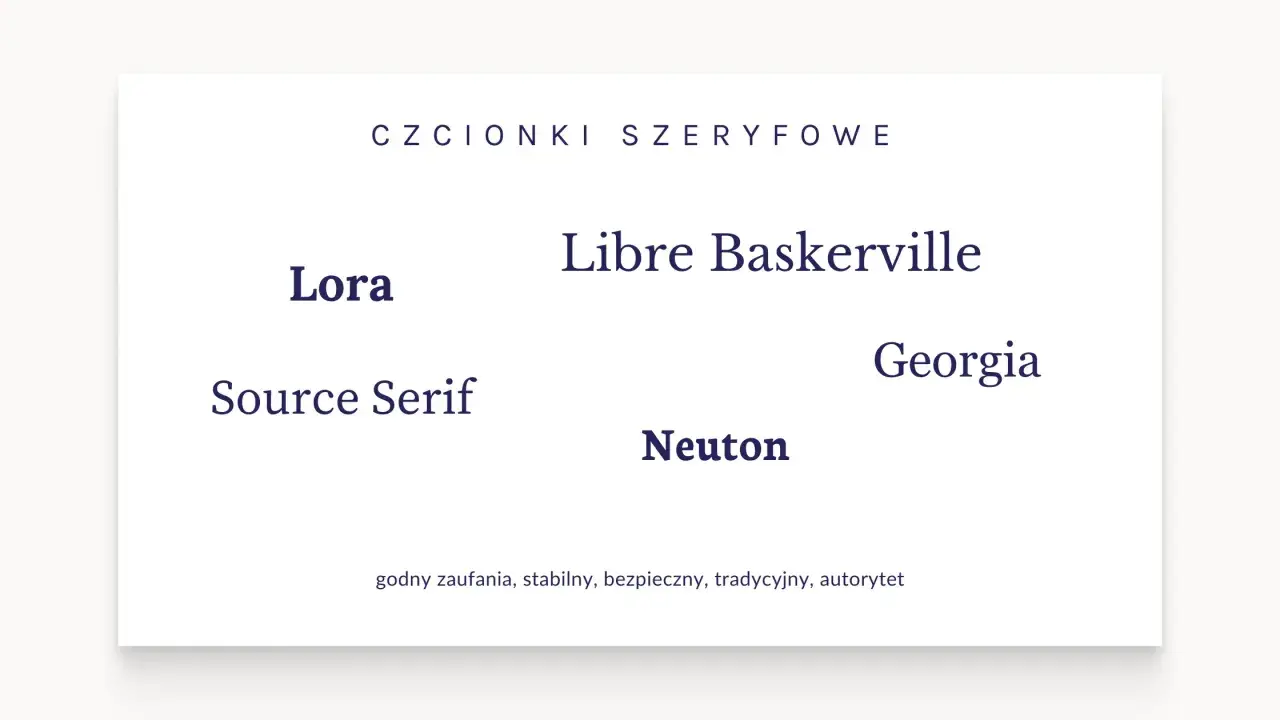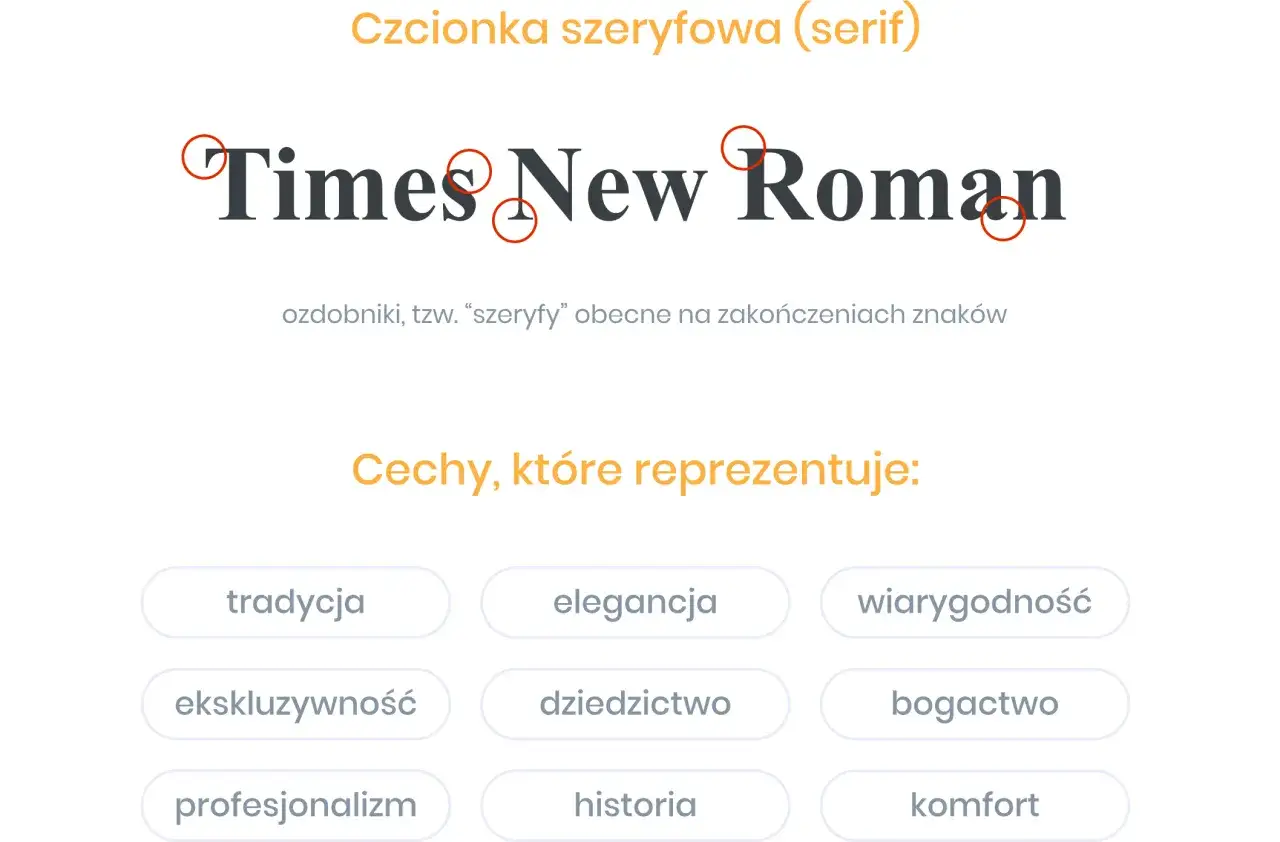
Najważniejsze różnice sprowadzają się do czytelności, tonu i medium
- Kroje szeryfowe mają ozdobne zakończenia liter i częściej kojarzą się z tradycją, elegancją oraz dłuższym czytaniem w druku.
- Kroje bezszeryfowe są prostsze wizualnie, zwykle lepiej sprawdzają się na ekranach, w interfejsach i w krótkich komunikatach.
- Odczyt zależy nie tylko od rodziny pisma, ale też od rozmiaru, kontrastu, interlinii i długości wiersza.
- W marketingu lokalnym serify dobrze budują charakter premium albo ekspercki, a bezszeryfowe litery dają szybkość i przejrzystość.
- Najlepsze efekty daje zwykle system z jednym krojem do nagłówków i jednym do tekstu, zamiast kilku podobnych fontów naraz.
Na czym naprawdę polega różnica między tymi rodzinami pisma
W typografii dokładniej mówi się o kroju pisma niż o czcionce, ale w języku marketingowym oba określenia często mieszają się ze sobą. Najprostsze rozróżnienie jest takie: serif ma małe zakończenia przy literach, a sans-serif ich nie ma. To nie jest jedynie detal wizualny. Ten detal wpływa na rytm czytania, charakter marki i na to, jak odbiorca ocenia tekst jeszcze przed przeczytaniem pierwszego zdania.| Cecha | Krój szeryfowy | Krój bezszeryfowy |
|---|---|---|
| Wygląd | Ma drobne zakończenia przy literach, przez co wygląda bardziej klasycznie. | Jest uproszczony, czysty i pozbawiony szeryfów. |
| Skojarzenia | Tradycja, wiarygodność, prestiż, doświadczenie. | Nowoczesność, prostota, neutralność, szybkość. |
| Najczęstsze użycie | Dłuższe teksty drukowane, materiały o bardziej editorialowym charakterze, marki premium. | Strony internetowe, aplikacje, szyldy, social media, krótkie komunikaty. |
| Potencjalne ryzyko | Przy małym rozmiarze i słabym ekranie może tracić czytelność. | Przy złym doborze bywa zbyt surowy albo „bezbarwny”. |
Najczęstszy błąd polega na traktowaniu tych dwóch rodzin jak prostego podziału na „lepszą” i „gorszą”. W praktyce liczy się kontekst: media, długość tekstu, grupa odbiorców i ton marki. Kiedy to rozróżnienie jest jasne, łatwiej ocenić, kiedy serif naprawdę pomaga, a kiedy tylko dodaje ciężaru. To prowadzi do pierwszego ważnego pytania: gdzie szeryfy faktycznie pracują na korzyść tekstu?
Kiedy krój szeryfowy pracuje na korzyść marki
Szeryfowy krój zwykle wygrywa tam, gdzie chcesz zbudować wrażenie doświadczenia, klasy i spokojniejszego rytmu czytania. Dobrze wygląda w materiałach drukowanych, w treściach o dłuższych akapitach i w komunikacji marek, które mają wyglądać dojrzalej, bardziej redakcyjnie albo premium. Adobe zwraca uwagę, że w dłuższym druku serify pomagają budować płynność czytania, zwłaszcza wtedy, gdy tekst ma trochę więcej miejsca i nie jest ściskany na małej powierzchni.
W praktyce widzę to najczęściej w takich zastosowaniach:
- księgarnie, wydawnictwa i blogi eksperckie, gdzie ważny jest spokojny, „czytelniczy” charakter,
- kancelarie, doradztwo i branże zbudowane na zaufaniu,
- hotele butikowe, restauracje z historią i marki rzemieślnicze,
- ulotki, katalogi i magazyny, w których tekst ma być bardziej elegancki niż krzykliwy.
Serif nie działa jednak automatycznie. Jeśli projekt jest zbyt mały, kontrast z tłem słaby albo papier niskiej jakości, ozdobne zakończenia mogą się zlewać i efekt zniknie. Wtedy krój, który miał dodawać szlachetności, zaczyna po prostu przeszkadzać. Właśnie dlatego w materiałach cyfrowych i krótkich komunikatach często lepiej sprawdza się podejście bardziej oszczędne.
Kiedy bezszeryfowy jest lepszym wyborem
Bezszeryfowy krój zwykle daje przewagę tam, gdzie odbiorca ma zrozumieć przekaz szybko, na małym ekranie albo z pewnej odległości. Canva przypomina, że na ekranach i w prostych układach sans-serif najczęściej wygrywa, bo daje czytelny, bezpośredni obraz bez dodatkowego szumu wizualnego. To dlatego tak często widzisz go w aplikacjach, na stronach firmowych, w interfejsach i w reklamach społecznościowych.W marketingu lokalnym bezszeryfowe litery są szczególnie mocne w sytuacjach takich jak:
- strona internetowa firmy, zwłaszcza na urządzeniach mobilnych,
- banery, szyldy i oznaczenia czytane z dystansu,
- grafiki do social mediów, gdzie komunikat musi „zaskoczyć” w sekundę,
- menu, cenniki i krótkie listy usług, które mają być przejrzyste, a nie dekoracyjne.
Nie chodzi przy tym o to, że każdy sans-serif jest zimny albo bezosobowy. Dobrze dobrany krój bezszeryfowy może być elegancki, miękki albo bardzo profesjonalny. Różnica polega raczej na tym, że bezszeryfowa forma częściej daje wrażenie prostoty i porządku, a to w wielu projektach przekłada się na szybsze zrozumienie treści. Gdy patrzę na lokalny biznes, rzadko pytam najpierw o „ładniejszy font”; częściej pytam, na jakim nośniku tekst ma pracować.
Jak dobrać krój do strony i materiałów lokalnej firmy
Jeśli prowadzisz restaurację, salon usługowy, gabinet albo sklep w swojej okolicy, typografia powinna wspierać to, co klient ma zrobić: zrozumieć ofertę, zaufać marce i podjąć kontakt. Dlatego wybór między serife[m] a bezszeryfowym krójm nie powinien zaczynać się od gustu, tylko od kanału komunikacji i rodzaju treści. Na stronie internetowej potrzebujesz czegoś innego niż na szyldzie, a w ulotce coś innego niż w poście reklamowym.| Materiał | Co zwykle działa najlepiej | Dlaczego |
|---|---|---|
| Strona główna i podstrony usług | Bezszeryfowy tekst podstawowy, ewentualnie szeryfowe akcenty w nagłówkach | Na ekranie liczy się szybki odczyt i czytelność na mobile. |
| Ulotka lub folder | Szeryfowy tekst dłuższy albo mieszanka serif + sans-serif | Druk daje większą swobodę, a tekst może wyglądać bardziej redakcyjnie. |
| Szyld i oznaczenia | Bezszeryfowy, mocny i prosty | Treść ma być zrozumiała z daleka i bez wysiłku. |
| Menu, cennik, oferta | Najczęściej bezszeryfowy, z wyraźną hierarchią | Klient skanuje informacje, więc porządek jest ważniejszy niż ozdobność. |
| Logo | Zależy od charakteru marki | Logo ma opowiadać o firmie, a nie podlegać jednej sztywnej regule. |
| Posty reklamowe | Bezszeryfowy nagłówek i krótki tekst | Na platformach społecznościowych wygrywa prostota i tempo odbioru. |
W praktyce zaczynam od trzech liczb: 16-18 px dla tekstu głównego na stronie, interlinii na poziomie 1.4-1.7 oraz maksymalnie dwóch rodzin pisma w jednym projekcie. Jeśli projekt ma być bardziej „premium”, mogę podnieść kontrast między nagłówkami a tekstem. Jeśli ma być użytkowy i szybki, wybieram prostszy układ, bez ozdobników, które tylko spowalniają odbiór. Kiedy ten dobór jest już ustawiony, trzeba jeszcze zadbać o to, żeby oba style nie zaczęły ze sobą rywalizować.
Jak łączyć oba style bez chaosu
Najbezpieczniejsze zestawienie to takie, w którym jeden krój prowadzi, a drugi wspiera. Najczęściej oznacza to nagłówek w bardziej charakterystycznym kroju i tekst podstawowy w neutralnym, bardzo czytelnym sans-serifze albo odwrotnie, jeśli marka ma bardziej nowoczesny profil. Nie trzeba szukać efektu za wszelką cenę. Dobrze dobrany duet fontów ma przede wszystkim porządkować treść, a nie przyciągać uwagę samą siebie.
- Serif + neutralny sans-serif dobrze sprawdza się w treściach eksperckich, premium i redakcyjnych.
- Sans-serif + serif bywa dobry, gdy marka chce wyglądać nowocześnie, ale nie sucho.
- Jedna rodzina z kilkoma wagami to najprostsze rozwiązanie, jeśli zależy Ci na spójności i łatwym wdrożeniu.
- Różnica charakterów jest ważniejsza niż sama moda na konkretny font.
- Unikaj dwóch podobnych krojów, bo zamiast hierarchii dostajesz wizualny bałagan.
Ja zwykle pilnuję jeszcze jednej zasady: nie dobieram krojów wyłącznie po tym, czy „ładnie wyglądają obok siebie” w próbce. Sprawdzam je w prawdziwej treści, z nagłówkiem, akapitem, numerem telefonu i krótkim CTA. Jeśli tekst wciąż jest czytelny po dodaniu rzeczywistych informacji, zestaw ma sens. Jeśli nie, nawet świetny font nie uratuje projektu. To właśnie taki test najczęściej odsłania ostatnie błędy.
Co sprawdzam przed publikacją, żeby typografia pracowała na treść
Przed oddaniem projektu do druku albo publikacją online przechodzę przez prostą listę kontroli. Nie jest efektowna, ale oszczędza sporo czasu i poprawek. To tutaj wychodzi, czy wybrany krój rzeczywiście wspiera komunikat, czy tylko dobrze wyglądał w próbce.
- Czy tekst ma wystarczający kontrast względem tła, także na telefonie?
- Czy wiersze nie są za długie i nie męczą wzroku po kilku linijkach?
- Czy nagłówki są wyraźnie mocniejsze od tekstu podstawowego, nie tylko większe?
- Czy interlinia daje oddech, zamiast ściskać akapity?
- Czy w całym projekcie nie ma więcej niż 2 rodzin pisma i 3-4 warianty wag?
- Czy charakter kroju pasuje do tonu marki: spokojnego, premium, technicznego albo przyjaznego?
Jeśli mam zostawić jedną praktyczną zasadę, to taką: nie wybieram kroju dlatego, że jest „ładny”, tylko dlatego, że pasuje do medium, skali i osobowości marki. Przy lokalnym biznesie najlepiej działa typografia, która jest czytelna na telefonie, spójna z szyldem i uczciwa wobec charakteru firmy. Wtedy kroje szeryfowe albo bezszeryfowe nie są ozdobą samą w sobie, ale narzędziem, które realnie pomaga sprzedać uwagę i zbudować zaufanie.